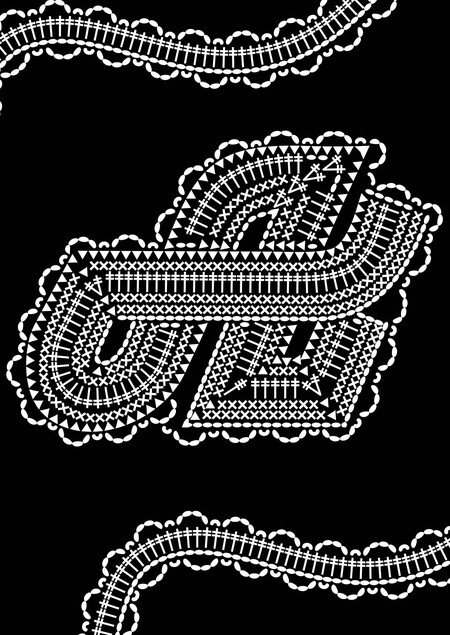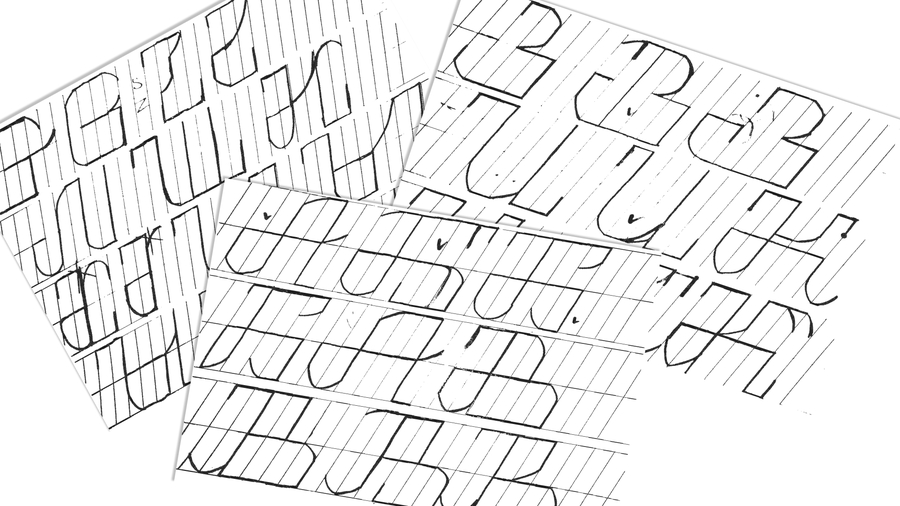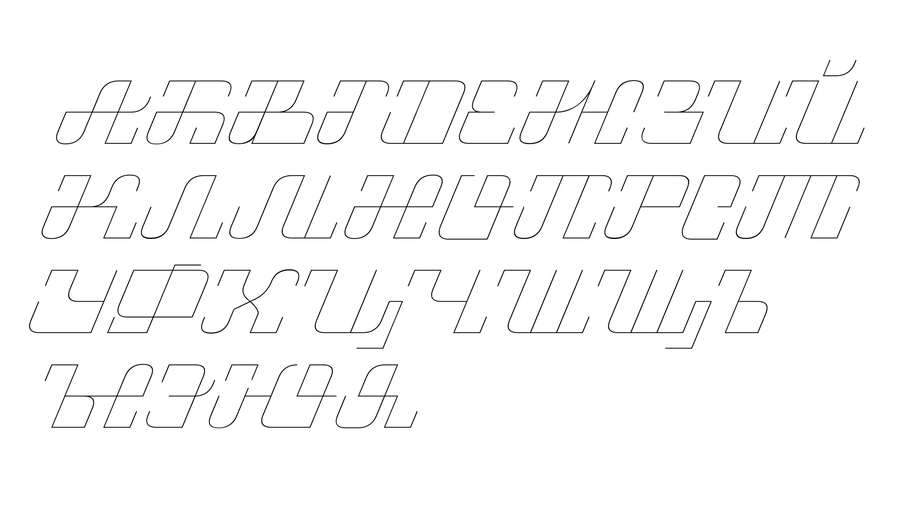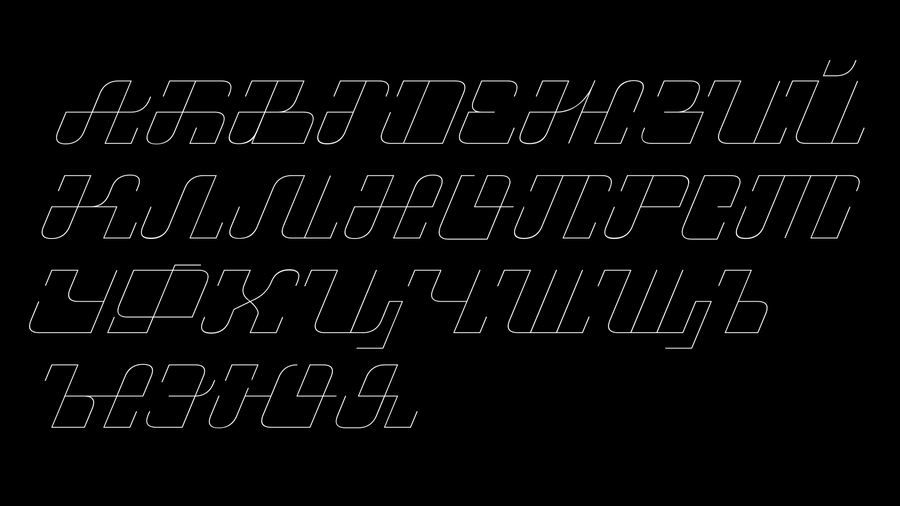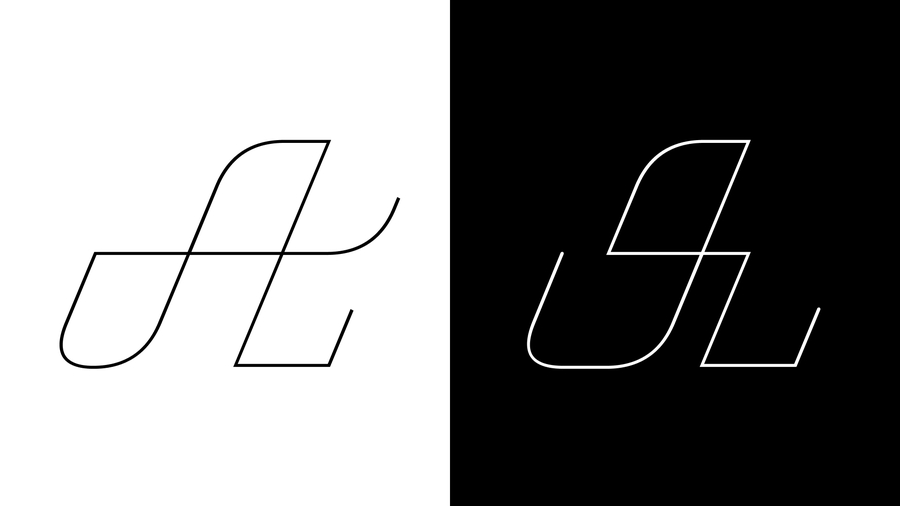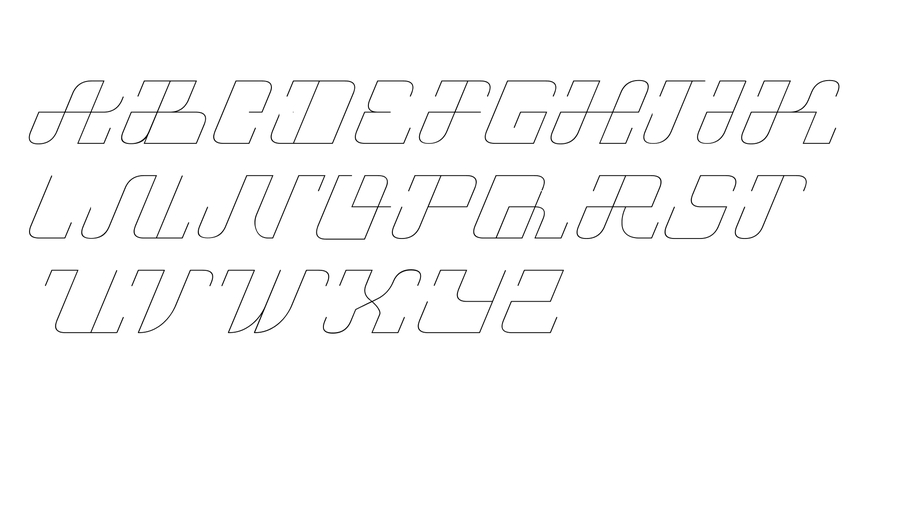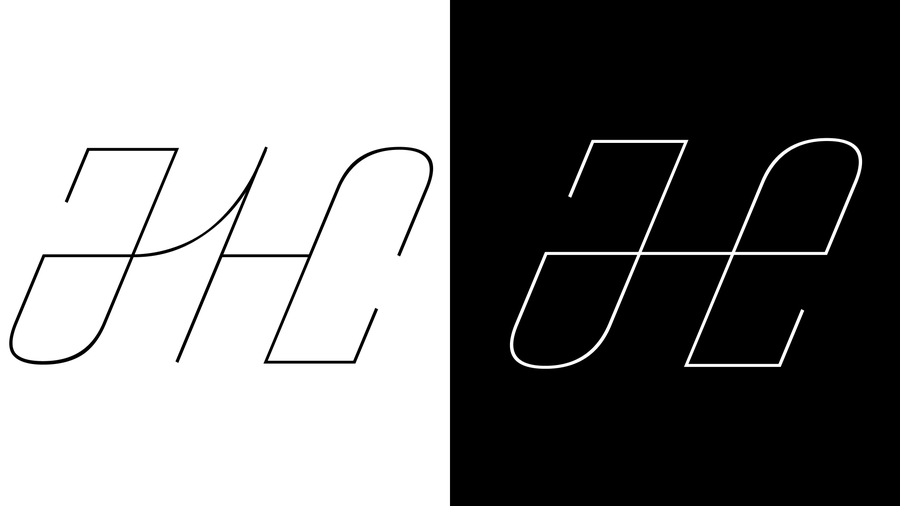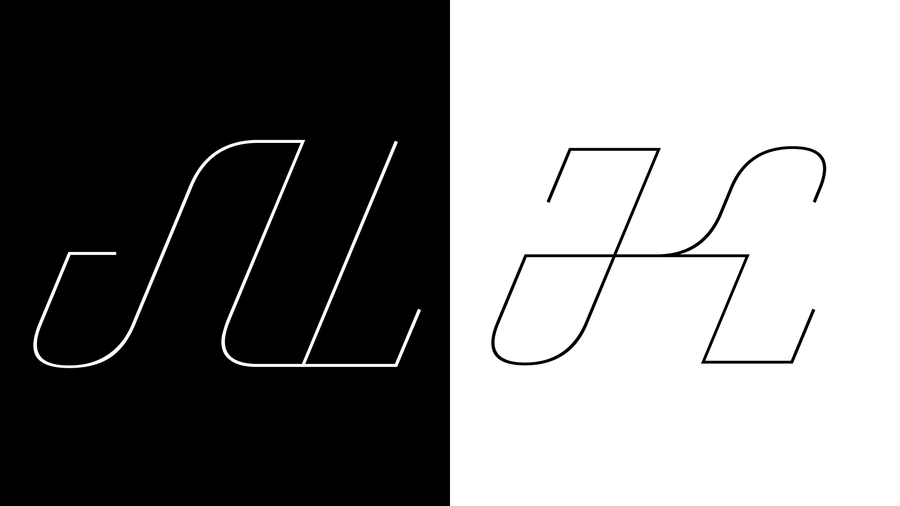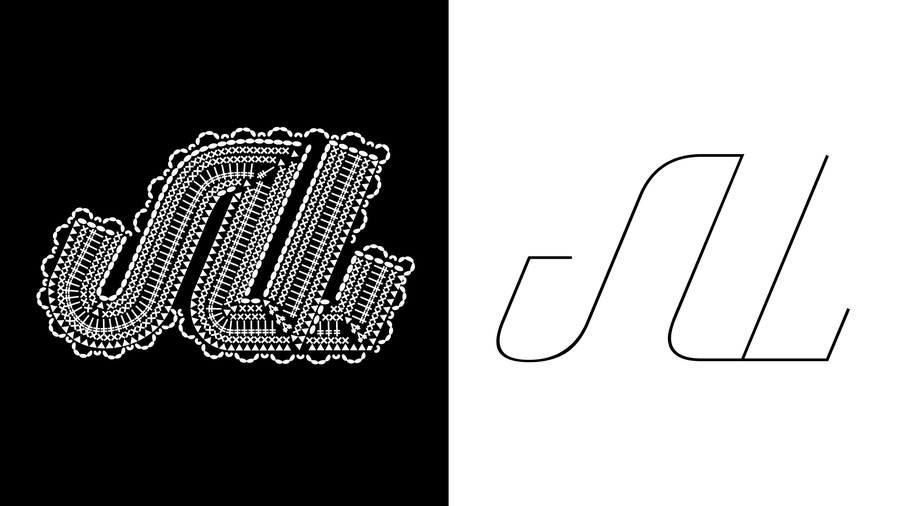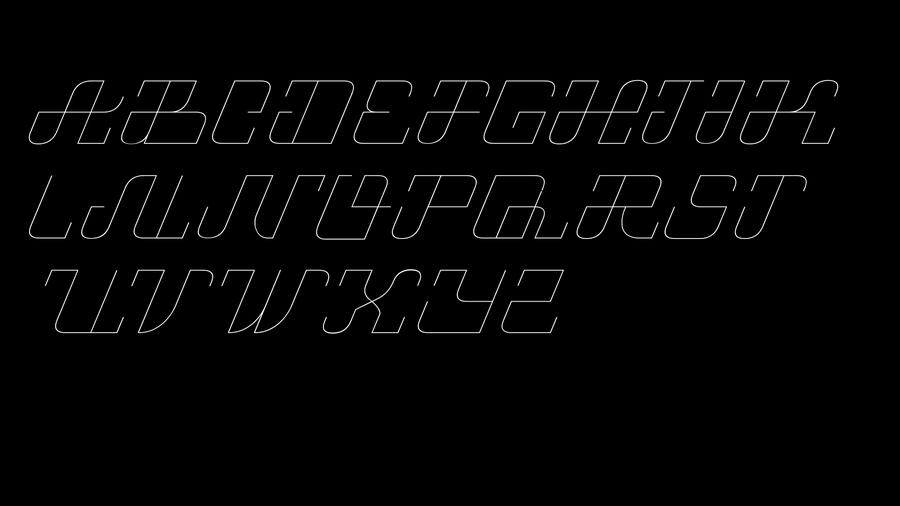
Chainstitch — это шрифт, сплетающий в одно целое две системы знаков: строгую геометрию советских школьных прописей и графический язык схем для вязания крючком. Каждая буква собирается из петель и столбиков, превращая набор текста в акт рукоделия. Шрифт — это ностальгия по тёплой, сделанной вручную эстетике в мире цифровой типографики, где строгость линий встречается с домашним уютом.
Шрифт предлагает орнаментальное начертание, где каждая буква украшена символами, позаимствованными из схем для вязания крючком. Этот вариант превращает текст в сложный узор.